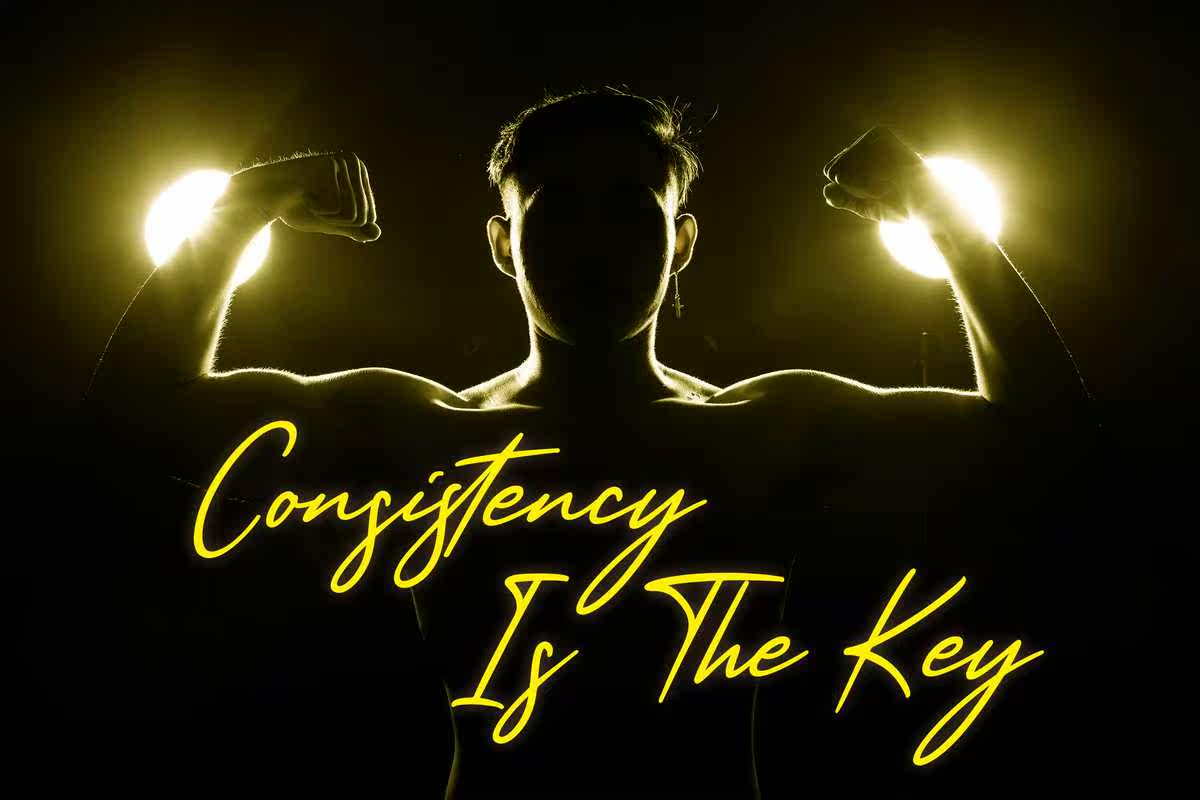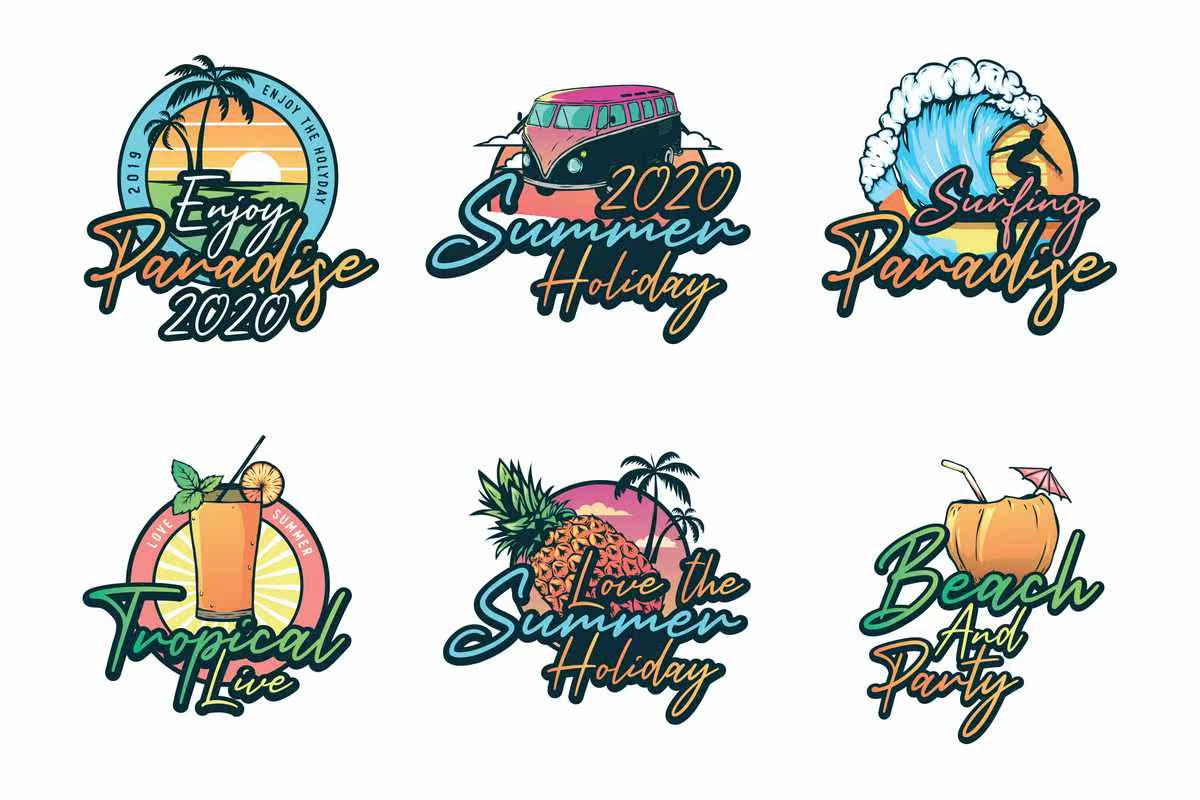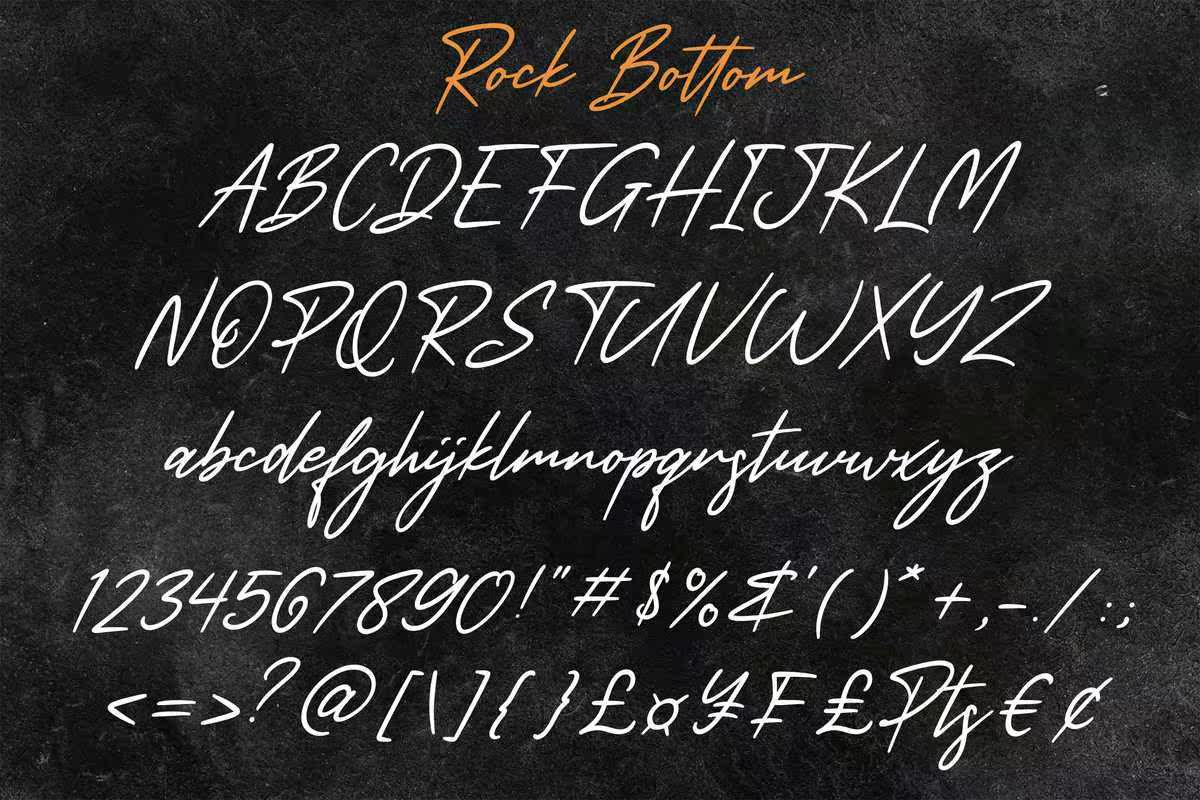
Rockbottom是一款流畅的书写字体,由LegantTouch描述,非常适合您喜爱的项目。爱上它令人难以置信的独特和永恒的风格,并使用它来创建壮观的设计!Rockbottom是一款流畅的书写字体,由LegantTouch描述,非常适合您喜爱的项目。爱上它令人难以置信的独特和永恒的风格,并使用它来创建壮观的设计!